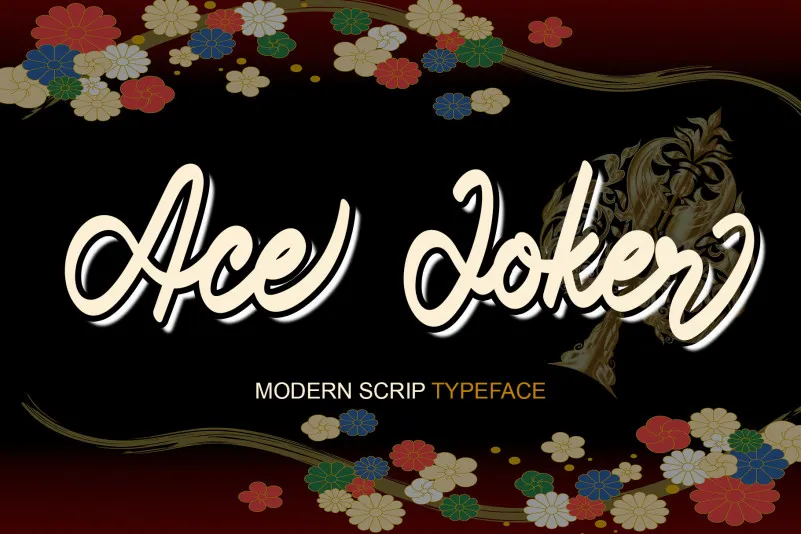
Ace Joker Font – Download Grátis
Este é um belo, versátil e flexível estilo tipográfico a mão escrita. Com seu ar quente, peculiar e alegre, este font será uma excelente companhia para cada ideia de projeto que você terá. Ele irá transformar suas ideias mais simples em obras de arte completas. Quer experimentar? Esta bela fonte vai te proporcionar horas de diversão explorando suas infinitas variações. Para quem ama a mão escrita e adora explorar novos estilos, este será o seu novo amigo no trabalho com texto. Aproveite para criar algo autêntico e único com esta aceatosa fonte que encanta os olhos.